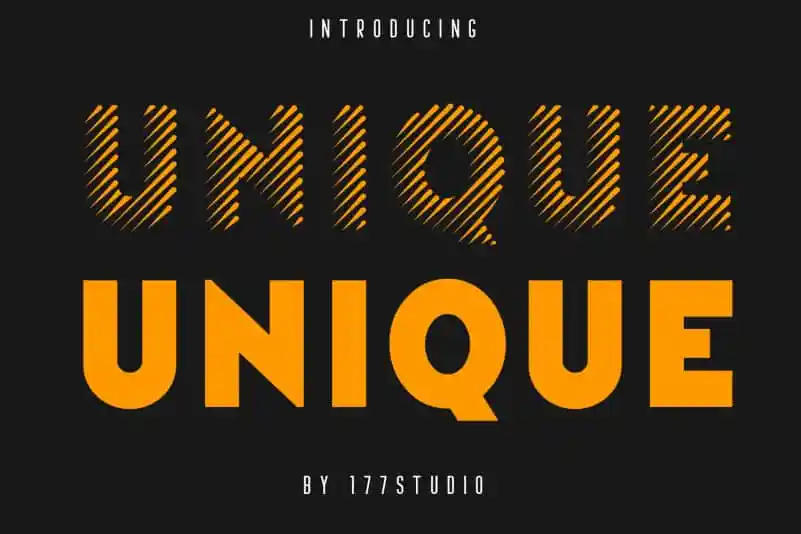
A fonte ‘Unique Stripes Font’ é uma escolha perfeita para quem procura um recurso visual impactante e moderno. Esta fonte está disponível na categoria de fonts display, criada pelo designer 177Studio. O design extra-loud da Unique Stripes fornece uma intensidade que se adequa a vários usos, sendo especialmente indicada para aplicações visuais em mídia digital. Ela é um bold halftone striped modern font, apresentando linhas retas e curvadas perfeitamente arredondadas, criando um design minimalista mas poderoso. Para designers que desejam transmitir uma forte mensagem visual, a Unique Stripes não tem o hábito de se esquivar da atenção. É uma opção ideal para estilos digitais modernos e revolucionários. Não espere mais – instale a fonte ‘Unique Stripes Font’ no seu próximo projeto para garantir que suas mensagens tenham um impacto indelével.